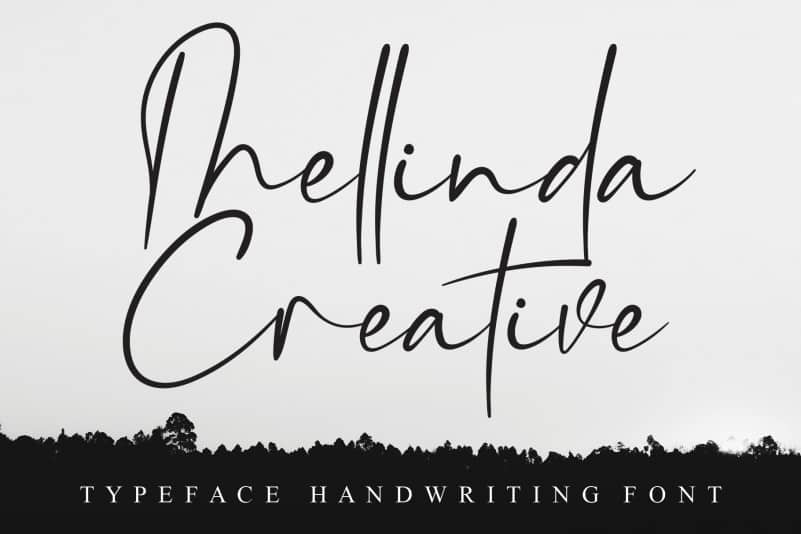
Mellinda Creative Script Font – Download Grátis
A Mellinda Creative Script Font é uma fonte criada para quem valoriza a arte do texto manuscrito na sua produção visual. Conhecida por seu estilo fresco e moderno, essa fonte vai proporcionar um toque especial em qualquer projeto onde ela for usada – seja para as notas de publicidade em uma campanha de marketing, ou como o design de etiquetas para os seus produtos finais. Ideal para criações artísticas, a Mellinda Creative Script é perfeita para projetos que exigem um toque elegante e único. Suas letras curvas fluidas são uma escolha ideal para trabalhos onde há uma necessidade de criar um contato pessoal com o consumidor – desde anúncios em plataformas sociais até cartões de convite, embalagens de produtos e etiquetas. Além disso, a fonte também é perfeita para adicionar um toque único à sua fotografia, como marca d’água ou logo, proporcionando o equilíbrio e sofisticação que tanto valorizamos em nossos designs digitais. A cada caractere criado por andikastudio nesta fonte hand-writed é uma história de design com elementos únicos. A Mellinda Creative Script Font oferece a você um produto personalizado para todos os seus projetos, ajudando-o a destacar sua marca e criar uma conexão emocional entre seu produto e o consumidor.